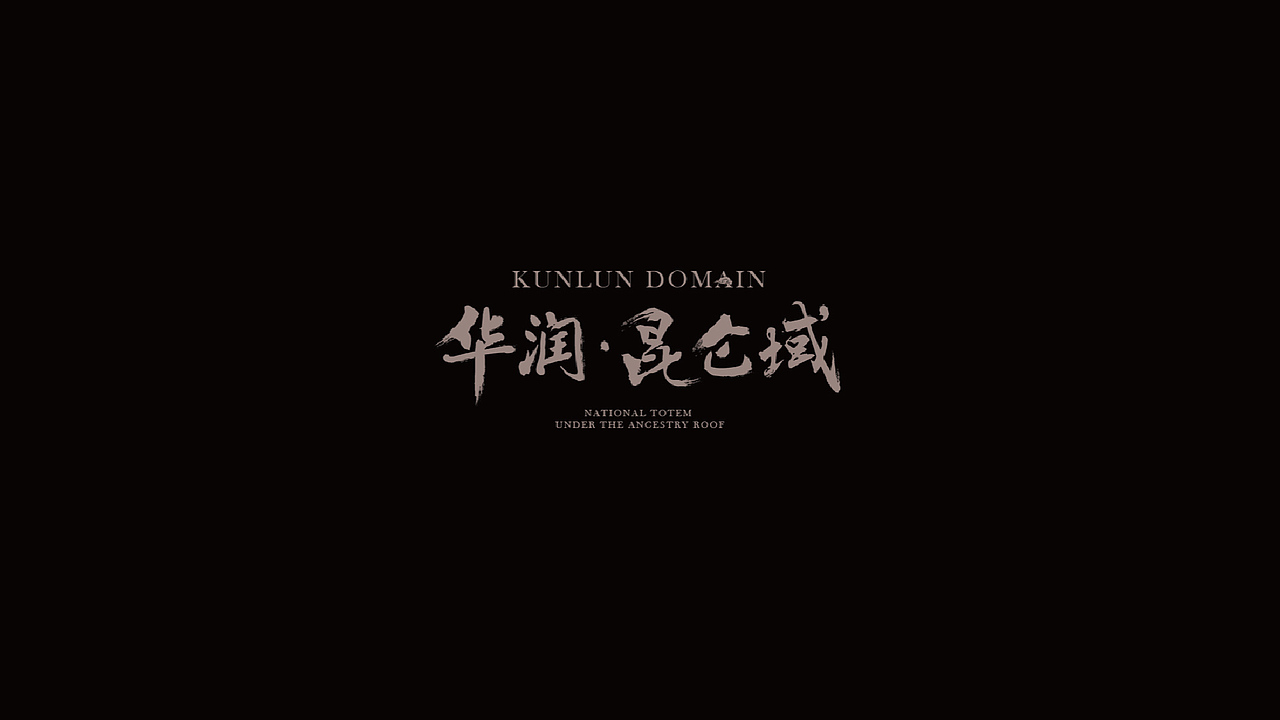
华润置地昆仑域项目,地处京城南二环,传承文化的豪宅项目。如何从出众多豪宅房产视觉中寻找差异化呢?根据一系列背书发现北京南城的文化属性,有着出众的人生经历、领略过大千世界的繁华,但心中依然怀着中国文化传承的高知人群是我们锁定的目标客群,他们不追求奢华浮夸的外在,而着眼于缓慢从容的生活节奏。
👆logo以书法字型为基础结合笔触做变化,使字体富有韵律的同时让笔法更挺劲
👆主KV是以“昆仑域”为基础形,结合气势磅礴的山脉、人文气息、中式建筑等元素交汇融合设计
慢船:从容淡定的姿态。去:与时代同行的责任感。遵循着内心,等待着时间给予机会和责任